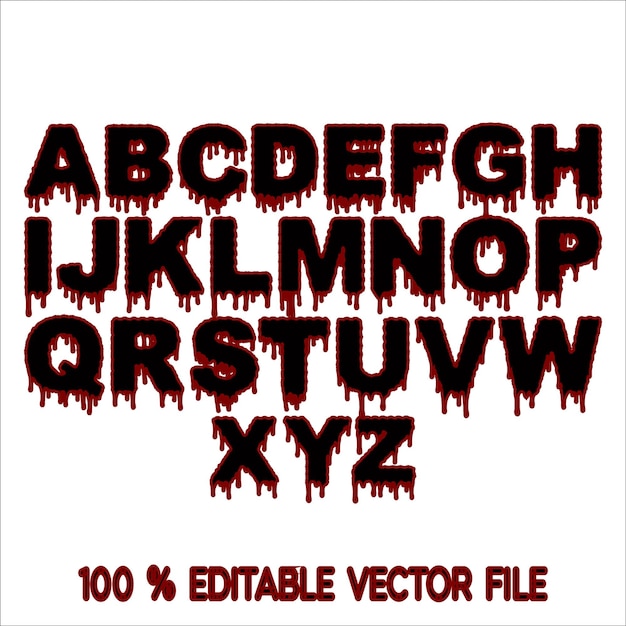
Halloween Dripping Alphabet Set Dripping Letters Set Driping Font Vector Design Splash Alphabet est un jeu d'alphabet d'Halloween qui est conçu pour être utilisé dans les jeux vidéo.